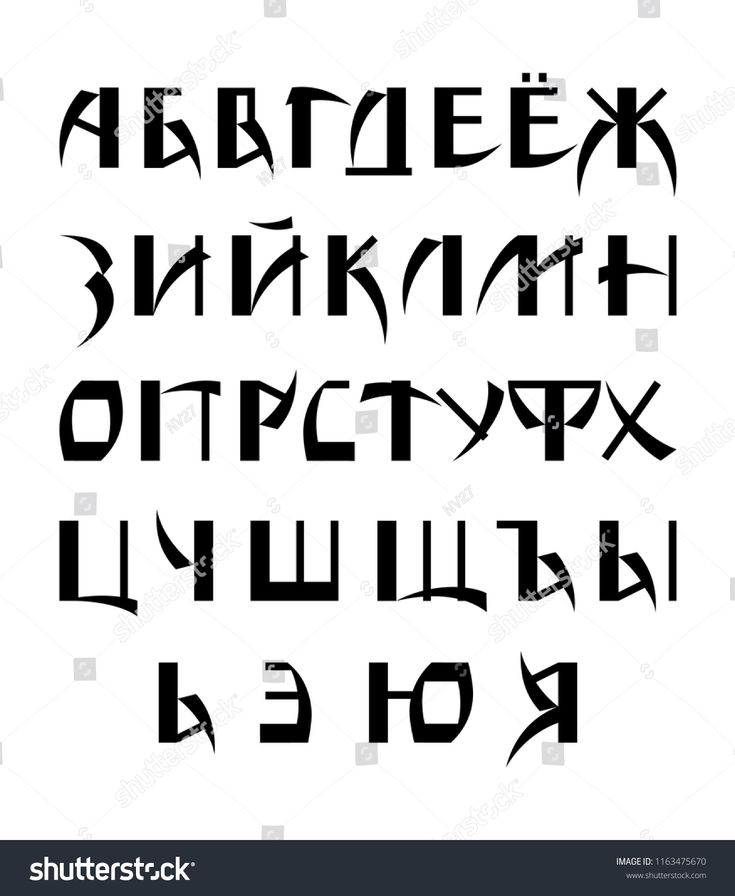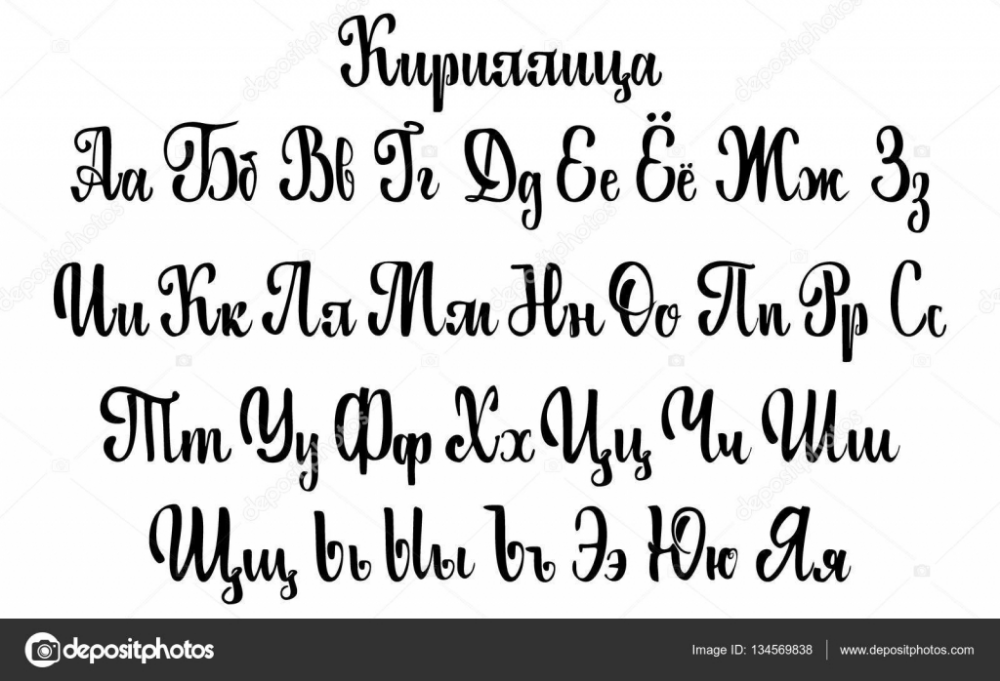
Шрифты русские современные. Лучшие бесплатные шрифты для дизайнеров. Поиск по начертанию
Из серии — пригодится. Коллекция русский (кириллических) шрифтов на все случаи жизни! Содержит более 5000 разных, не повторяющихся шрифтов с различными начертаниями. всего более 9000 файлов . Все шрифты разбиты на 5 основных раздела, что делает поиск нужного очень удобным.
Информация о коллекции шрифтов
Коллекция содержит 5000 русских шрифтов и 9000 начертаний . Найти среди такого количества нужный — задача не простая. Поэтому в программе присутствует три варианта поиска: по названию, по семействам, по начертанию.
Поиск по названию:
Если нужно найти конкретный известный шрифт — отправляйтесь в этот раздел. Здесь все шрифты диска перечислены в алфавитном порядке. Найти нужны не составит труда.
Поиск по семействам:
Если вы знаете, как выглядят символы нужного шрифта, но не знаете как он называется, поищите по семействам. Все шрифты одного семейства похожи начертанием символов, но отличаются наклоном, шириной, толщиной и прочим. Найдите близкое начертание и переходите на страницу с этим семейством, здесь вы найдете нужный шрифт.
Поиск по начертанию:
Поиск по начертанию подойдет, когда вы ещё не определились, какой шрифт Вам нужен, и хотите подобрать по внешнему виду. В этом разделе шрифты отсортированы по внешним признакам, и позволяют искать в небольшой группе.
В коллекцию шрифтов включены более 2700 файлов:
В коллекции представлено более 1000 рубленых кириллических шрифтов .
Какие шрифты включены в коллекцию (всего более 2000 файлов):
Название тут мало что может сказать о шрифте. Поэтому покажем лишь список групп:
Шфриты в веб-дизайне вещь практически незаменимая. Используя при разработке дизайна сайта нестандартные и оригинальные шрифты вы можете достичь поистине удивительного результата.
Все материалы разделены и скомпонованы в отдельные наборы по тем или иным тематикам — каллиграфические, готические, новогодние, оригинальные, рукописные и многие другие шрифты к вашим услугам. Я постараюсь отобрать и найти самые лучшие наборы шрифтов в интернете для публикации в Дизайн Маним. Постараюсь, чтобы вы могли скачать шрифты для фотошопа которые действительно пригодятся в работе, а не просто пополнят вашу и без того большую коллекцию шрифтов.
Что-то давно у нас не было оригинальных шрифтов в блоге. Последний пост и этой рубрики посвящался страшным хоррор шрифтам, которые легко можно использовать для открыток/иллюстраций на хеллоуин. Если же вам надо создать графику в азиатском стиле, то сегодняшняя подборка как раз для вас. Сначала будут материалы с англоязычным алфавитом, а после них — с поддержкой кириллицы. По аналогии со статьей про японские и китайские логотипы мы…
Как правило, крупные онлайновые каталоги шрифтов, например, такие как архивы шрифтов на русском языке не просто включают в себя файлы для скачивания, но и позволяют посмотреть входящие в них символы. Это удобно, когда вам требуется подобрать буквы, имеющие определенный специфический вид.